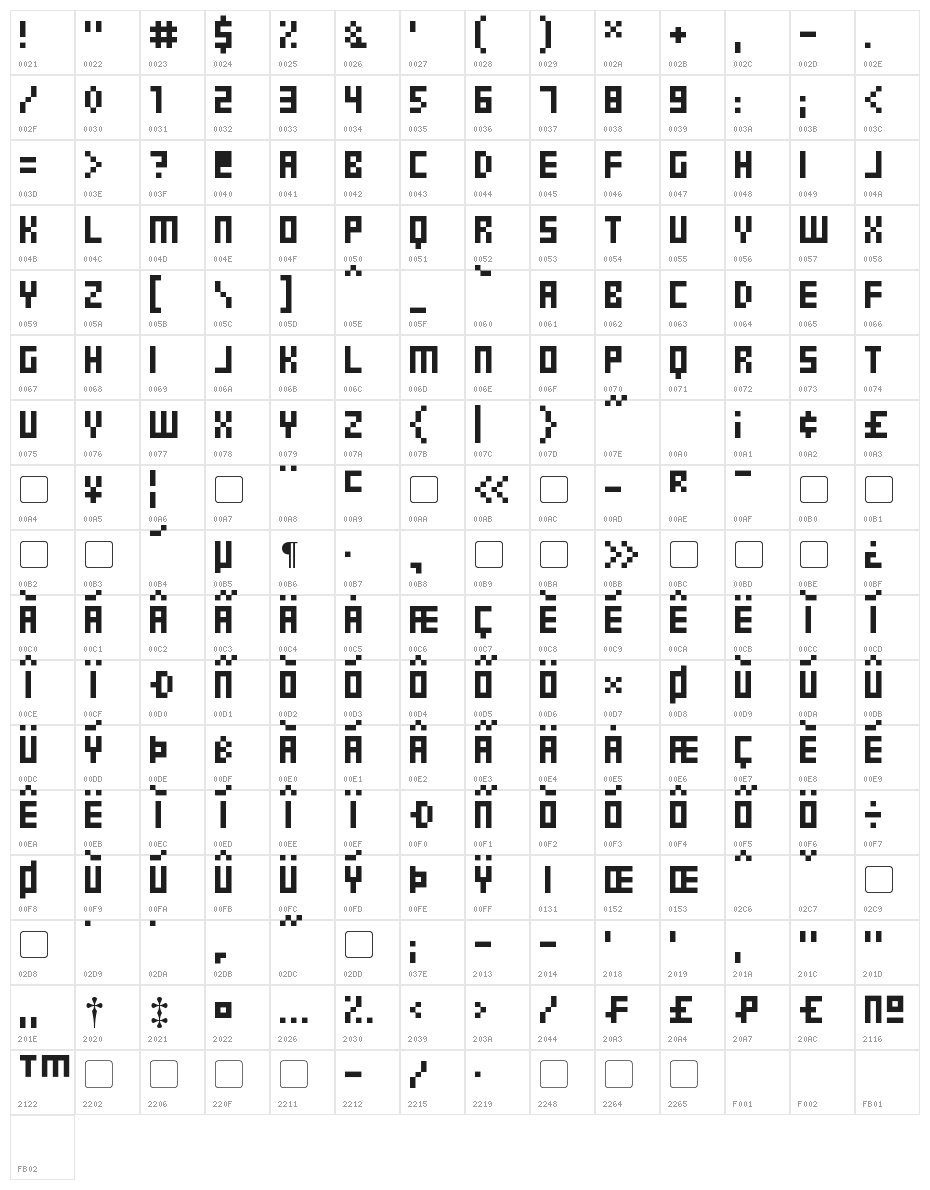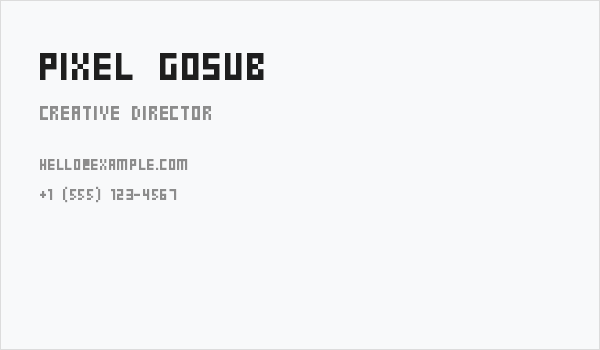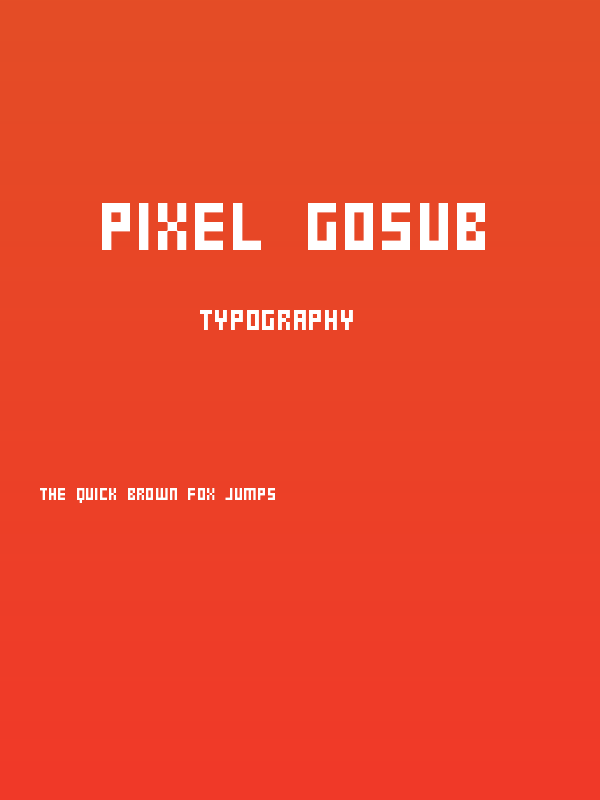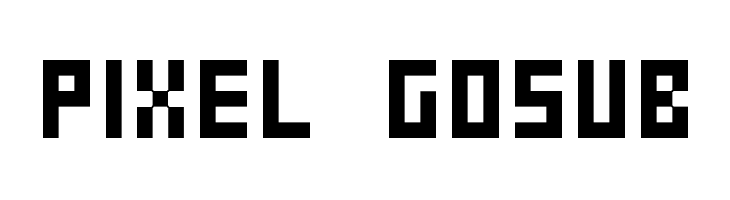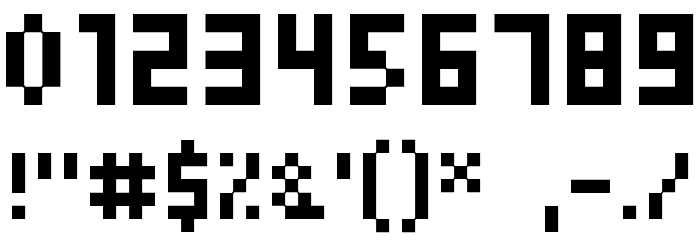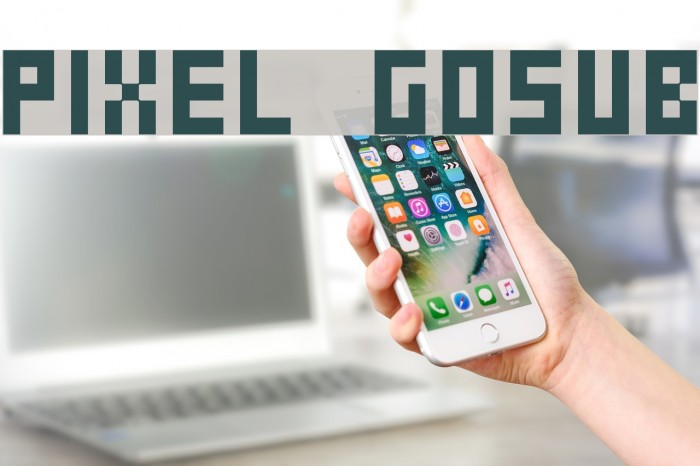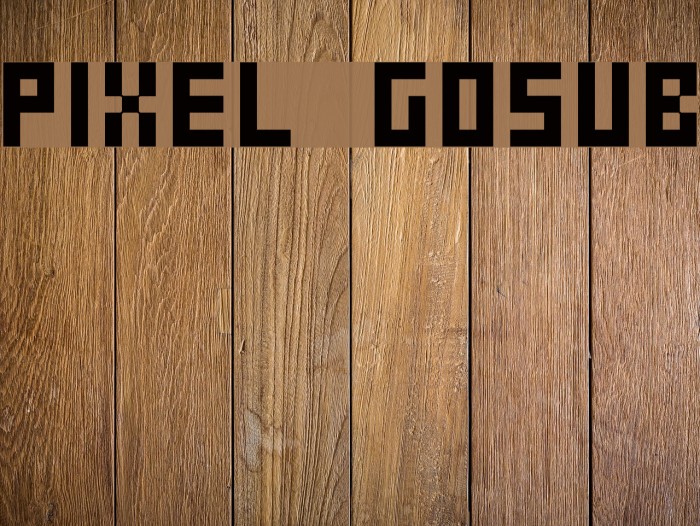
Pixel Gosub Font
| カテゴリ | Pixel |
| 用途 | Logos, Headlines, Digital Art |
| おすすめプロジェクト | Ideal for video game design, retro-themed posters, digital art projects, and any creative work that seeks to capture a vintage digital aesthetic. |